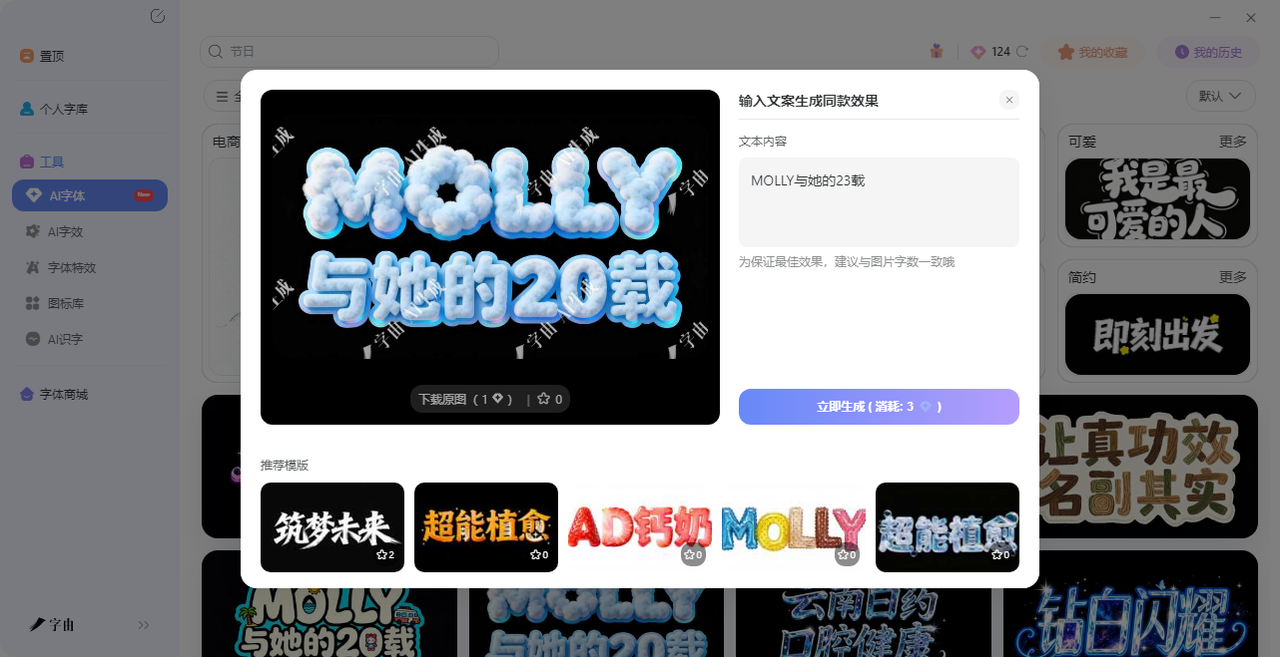
还在手动做艺术字?在线生成器帮你省时间
做海报封面、发社交媒体配图、设计Logo标题的时候,你是不是也遇到过这种情况:想在封面上放一行醒目的标题,但电脑自带的字体不是太普通就是太死板。打开PS调了半天内阴影、外发光、渐变叠加,出来的效果还是不满意。其实现在有很多在线艺术字生成工具,输入文字选个模板就能出图。今天整理了5个不同风格的在线艺术字生成器,覆盖了从简单复制粘贴到专业Logo设计的各种需求。输入文字,点一下生成,几分钟就能拿到能用的艺术字图。
字由是目前国内设计师用得最多的字体管理与AI字体平台之一,注册用户超过2000 万,和汉仪字库、蒙纳字库等头部厂商深度合作。它的AI字体功能藏在客户端顶部“AI工具”里,打开后你会看到一个模板库,目前提供了400多种字体特效模板,覆盖电商促销标题、游戏视觉设计、新媒体封面、品牌海报等不同场景。模板风格按国潮风、手写书法、科技感、霓虹灯、金属质感等分类排好了。
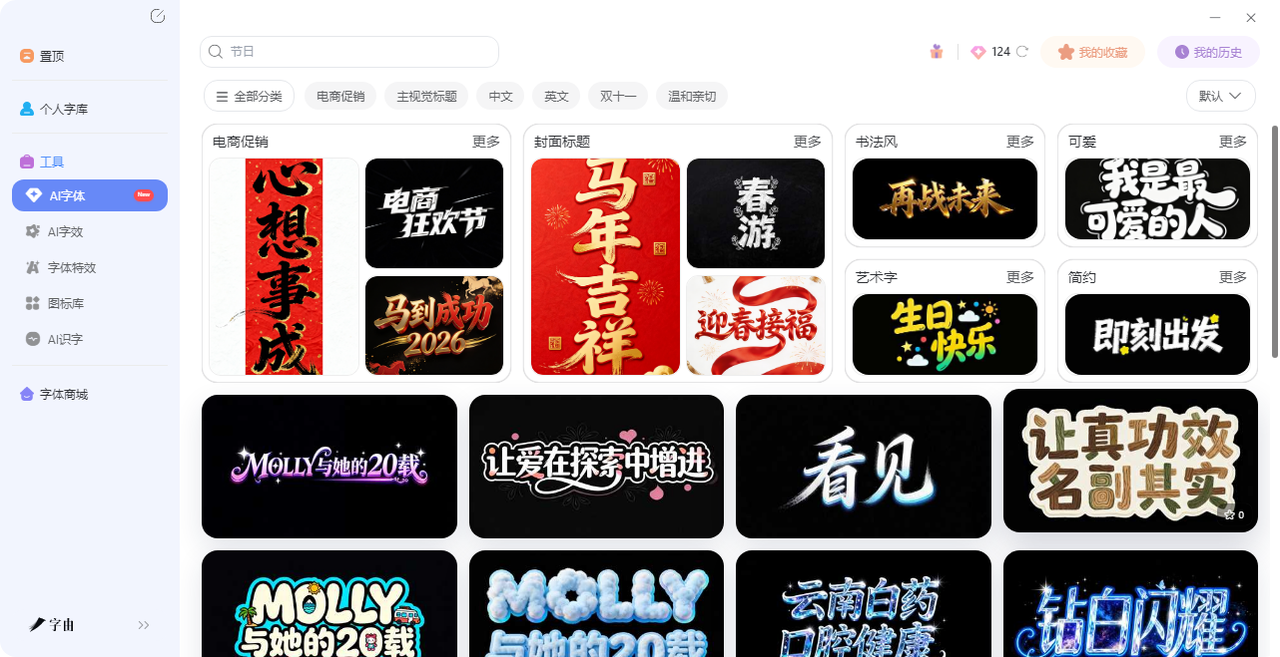
操作很简单:先根据场景筛选模板,比如要做一张国潮风海报,就在“风格”里选“国潮风”;找到喜欢的模板后点“做同款”,在右侧文本框里把模板里的文字换成你自己的文案;点“立即生成”,等待10到15秒,系统就会生成一张带有特效的艺术字图片。生成后可以下载PNG格式,默认背景透明,直接拖进PS、Canva、剪映里就能用。
2、Font Generator Art
第二个网站是Font Generator Art。从截图来看,它主打的是“Attitude”风格的装饰性字母转换。输入文字后,系统会生成多种带有装饰效果的字母样式,比如每个字母周围加小圆点、爱心等符号,生成的结果可以直接复制粘贴到社交媒体、游戏昵称或聊天框里。
这个工具的特色是“快”——不需要注册,不需要下载图片,输入文字就能看到多种样式,点一下复制就能用。它适合那些想要在文字上加一点小装饰、但又不想折腾复杂操作的用户。比如你想在朋友圈发一句带点个性的文案,或者给Discord昵称加点花样,Font Generator Art比打开设计软件方便太多。
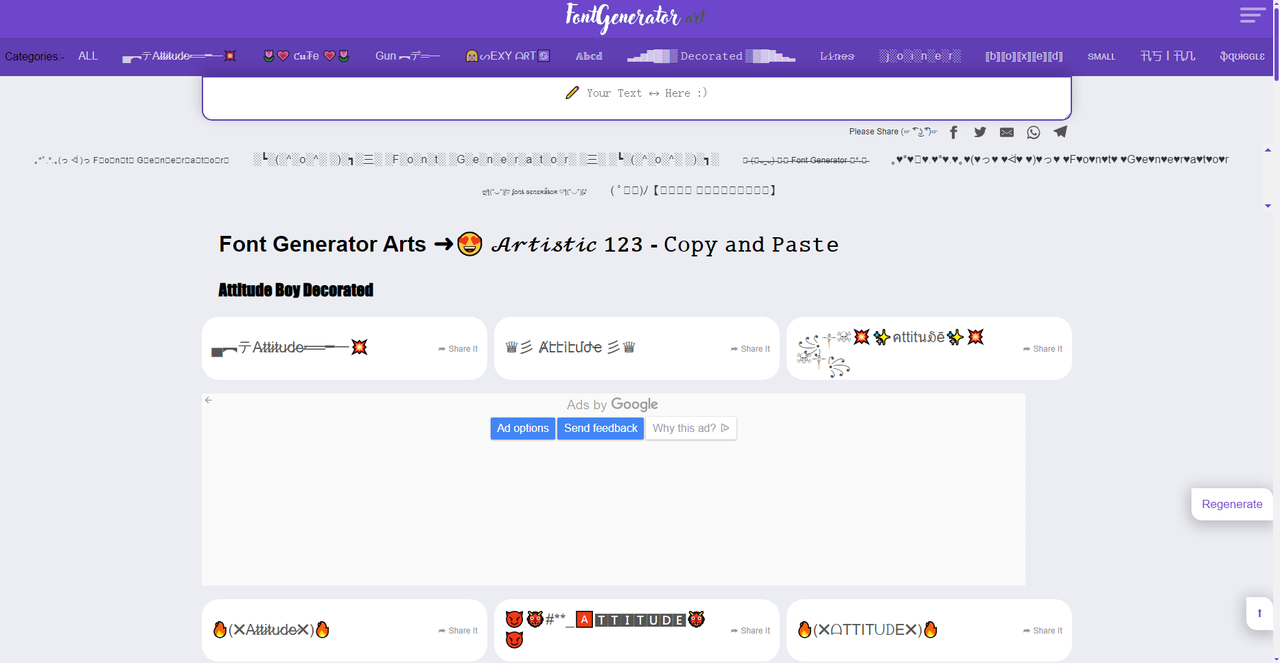
3、ArtFont
第三个工具是ArtFont。这是一个AI驱动的艺术字体生成平台,官方宣称拥有200多种专业模板,覆盖书法、涂鸦、优雅、可爱、霓虹、复古等多种风格。截图显示它的模板分类非常细:Calligraphy(书法)、Street Art(涂鸦)、Neon Glow(霓虹)、Elegant Minimal(极简优雅)、Retro(复古)等,每个分类下面都有多个模板,且标注了使用次数(比如2.1k、1.9k等)。
ArtFont的亮点在于生成质量:支持2K标准画质和4K可选画质,生成的PNG和JPG图片可以直接用于印刷或网页。它还提供实时预览功能,输入文字后可以实时看到AI生成的效果。操作流程和字由类似:选模板、输文字、生成、下载。如果你需要生成高质量的印刷级艺术字,ArtFont是一个值得尝试的备选。需要注意的是,ArtFont在中文模板的支持上可能不如字由丰富,更适合英文项目。
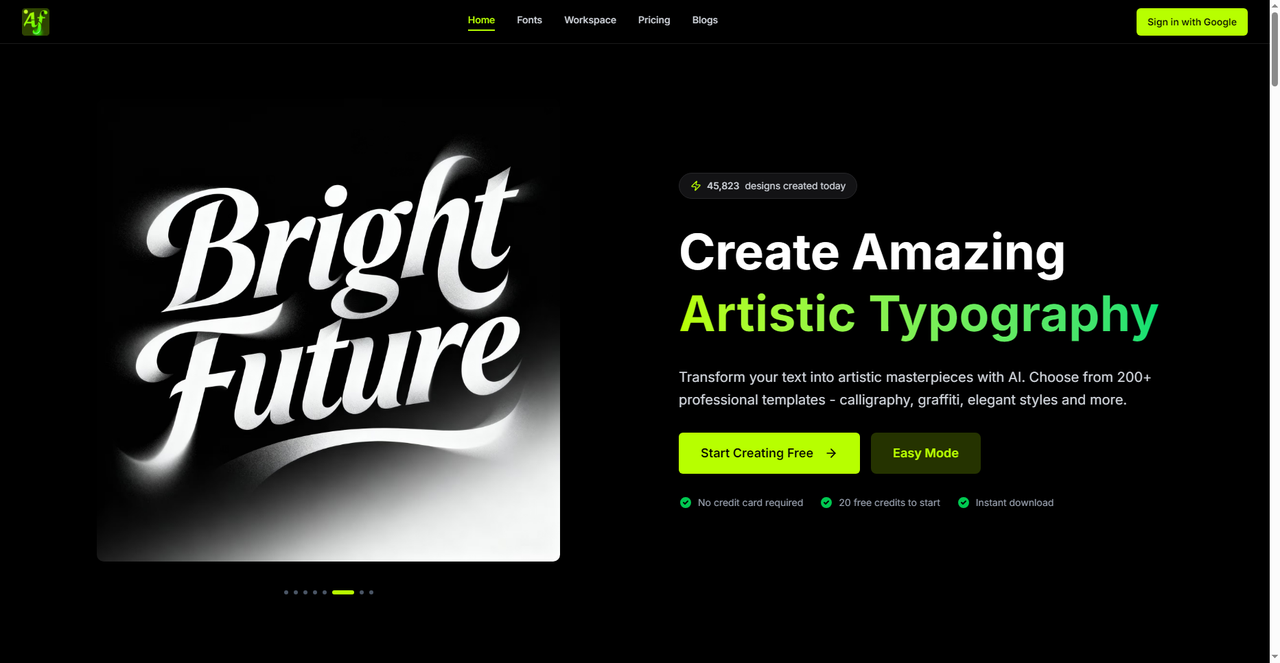
4、Gologo
第四个工具是Gologo这是一个中文的艺术字体在线生成器,主要面向Logo设计、海报、社交媒体封面、品牌标识等场景。它的核心功能是“输入名称,一键生成书法艺术字”,支持自定义布局(水平、垂直、环绕)和颜色(传统墨色、朱砂红、金色等)。Gologo的特色是偏重“书法风格”。如果你需要做一款中式风格的Logo、店铺招牌、或者带有传统文化气息的标题,Gologo的生成效果比普通花体字生成器更专业。生成后还可以在线编辑调整,支持下载矢量源文件。对于设计师和品牌方来说,矢量文件意味着可以无限放大不失真,用在印刷品上完全没问题。
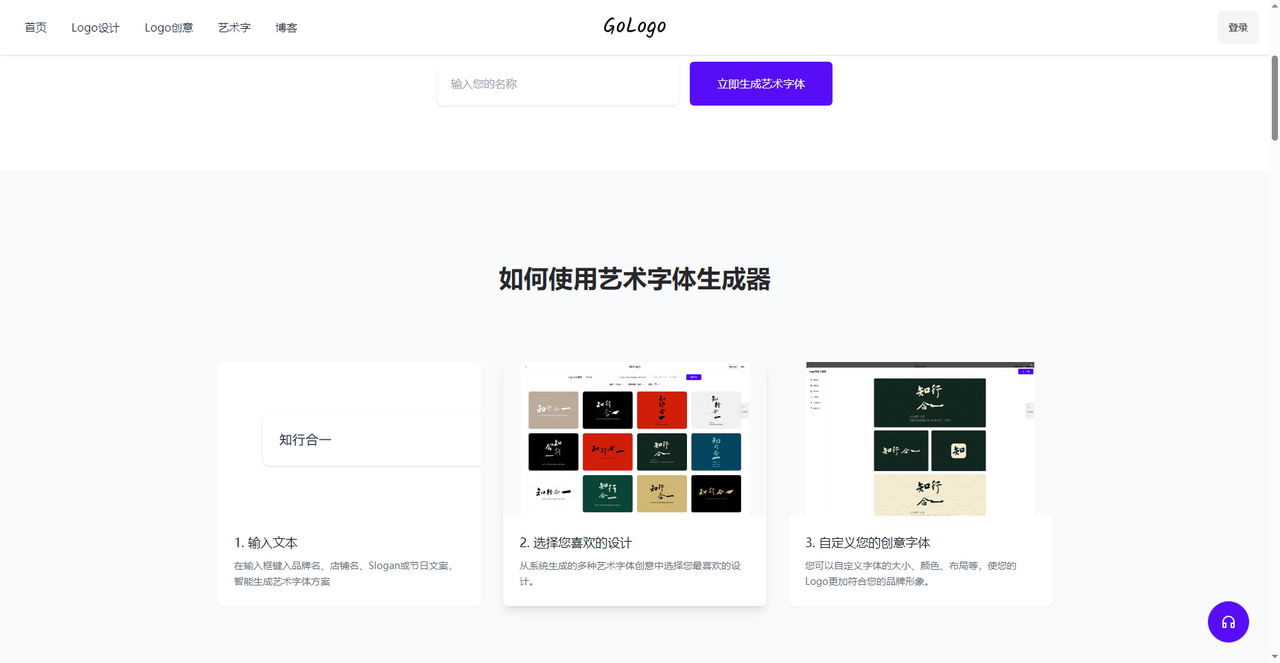
5、中文艺术字生成器
第五个工具是一个中文的在线艺术字生成器,它的特点是提供了丰富的参数调节选项:可以选字体(比如“凉如三月”这种艺术字体),调文字颜色、背景颜色、字体大小、旋转角度、图片宽度高度、字体投影开关、左右上下边距等。
输入文字后点击“生成”,就能看到预览效果,然后下载图片。这个工具适合那些“对花体字不满意,想要更自由控制”的用户——你可以自己搭配颜色和背景,让艺术字更贴合海报的整体风格。相比纯花体字生成器,它多了一些设计自由度,又比PS简单很多。如果你需要的不是简单的Unicode花体字,而是一张真正可以放在海报里的艺术字图片,这个生成器值得一试。
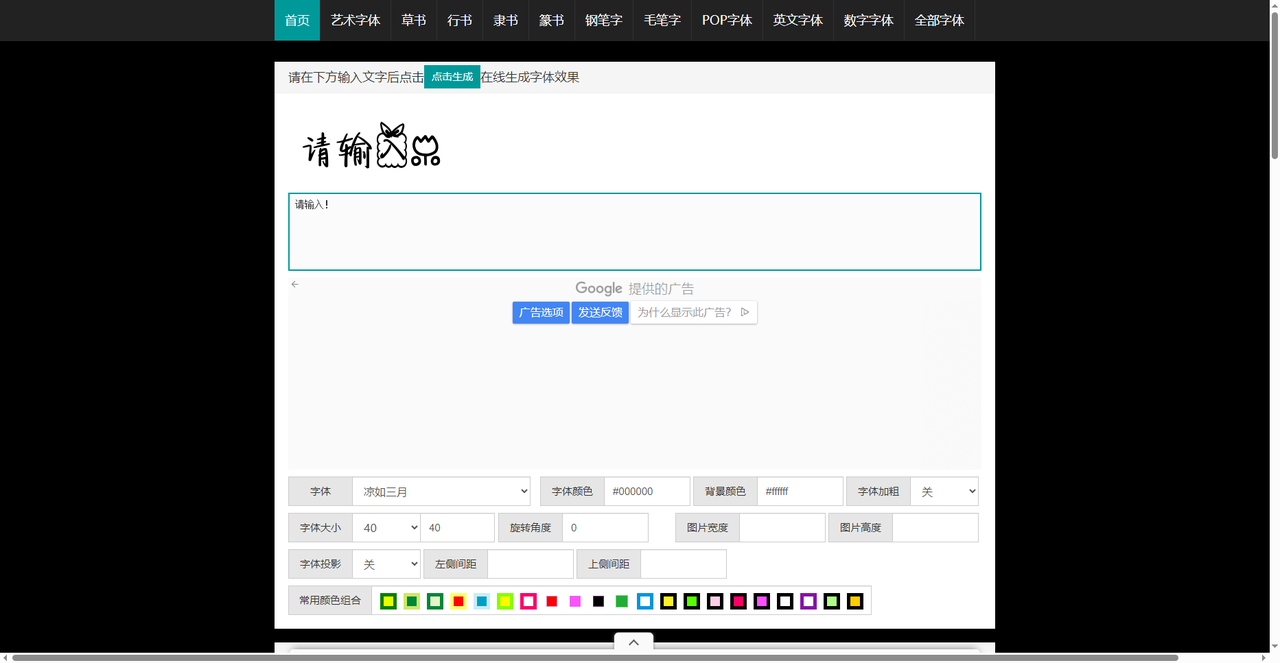
5个工具各有各的用法,字由最适合中文场景,400多种AI模板覆盖多种风格,10秒生成可商用艺术字图片;选哪个取决于你当下的需求——是做中文海报还是英文标题,是要图片还是纯文本,是要免费商用还是个人使用。这几个工具基本都是免费的,挨个试一遍,几分钟出一张图,总能找到适合你项目的那一款。